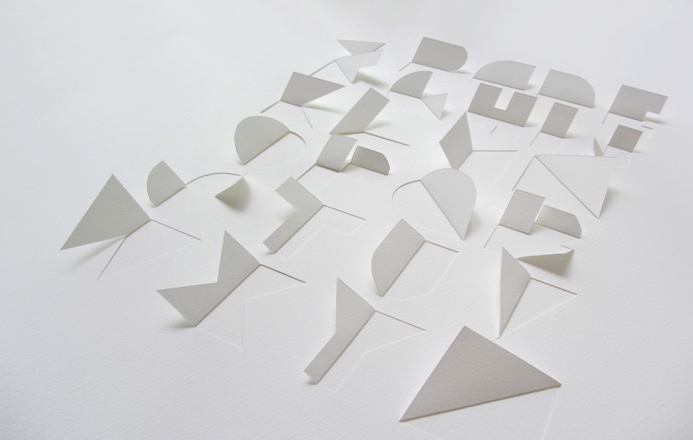
Gina Hollingsworth est une artiste typographe qui s'est appliquée à créer un alphabet typographique à partir d'une simple feuille de papier.
L'artiste a d'ailleurs reçu un prix suite à l'exposition de son travail qui présentait son oeuvre au complet à Londres, lors du Graphic Design Summer School